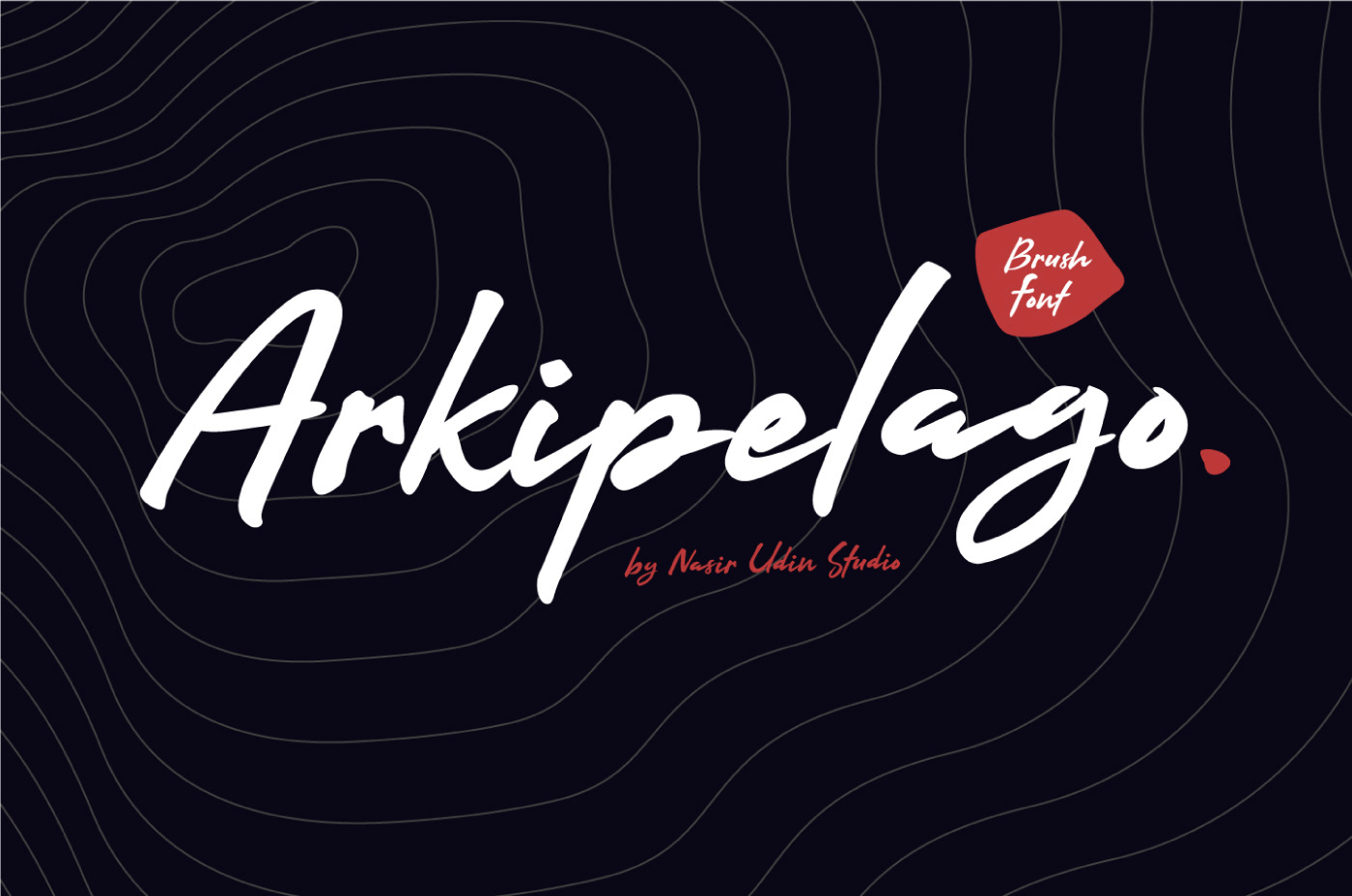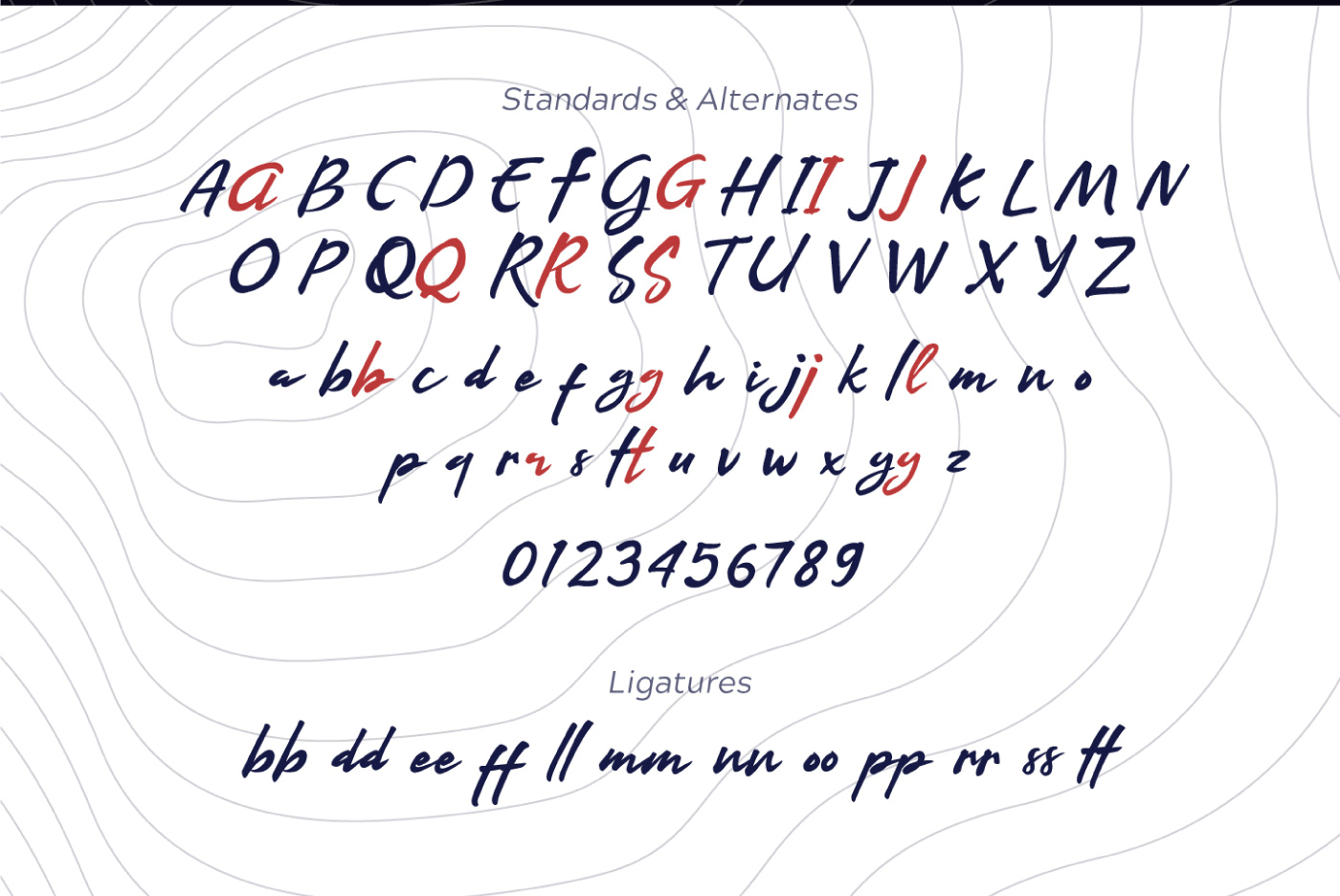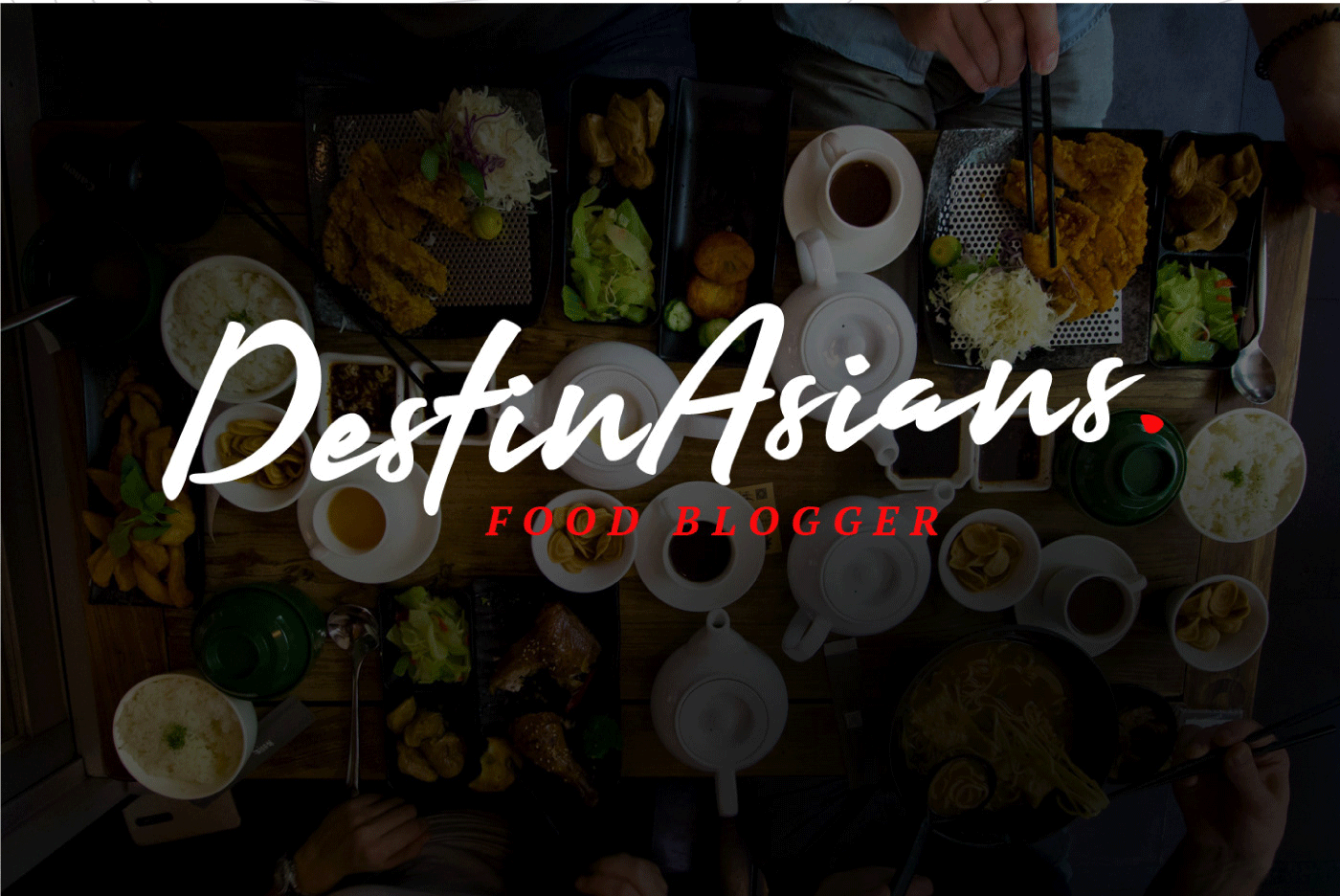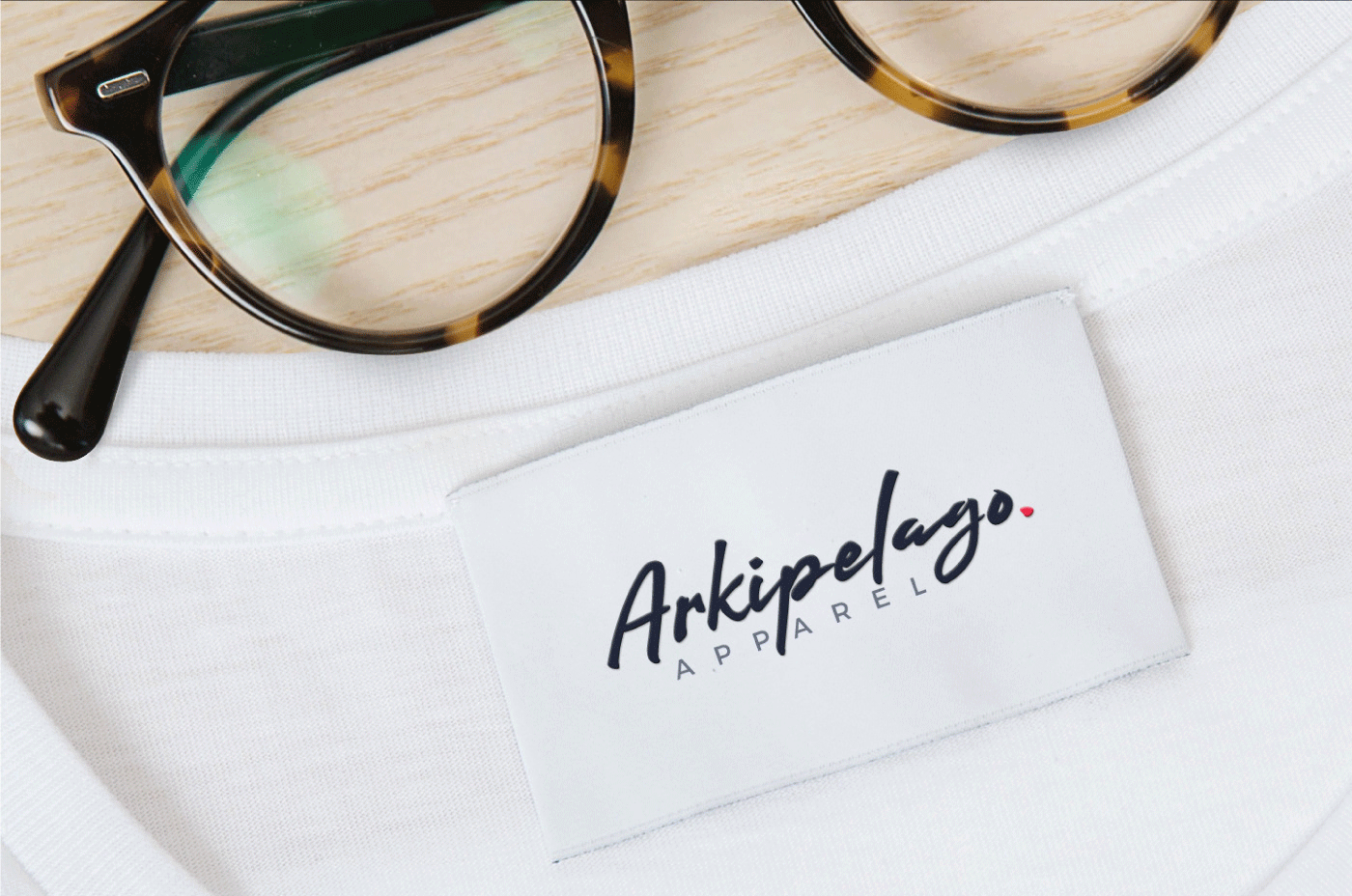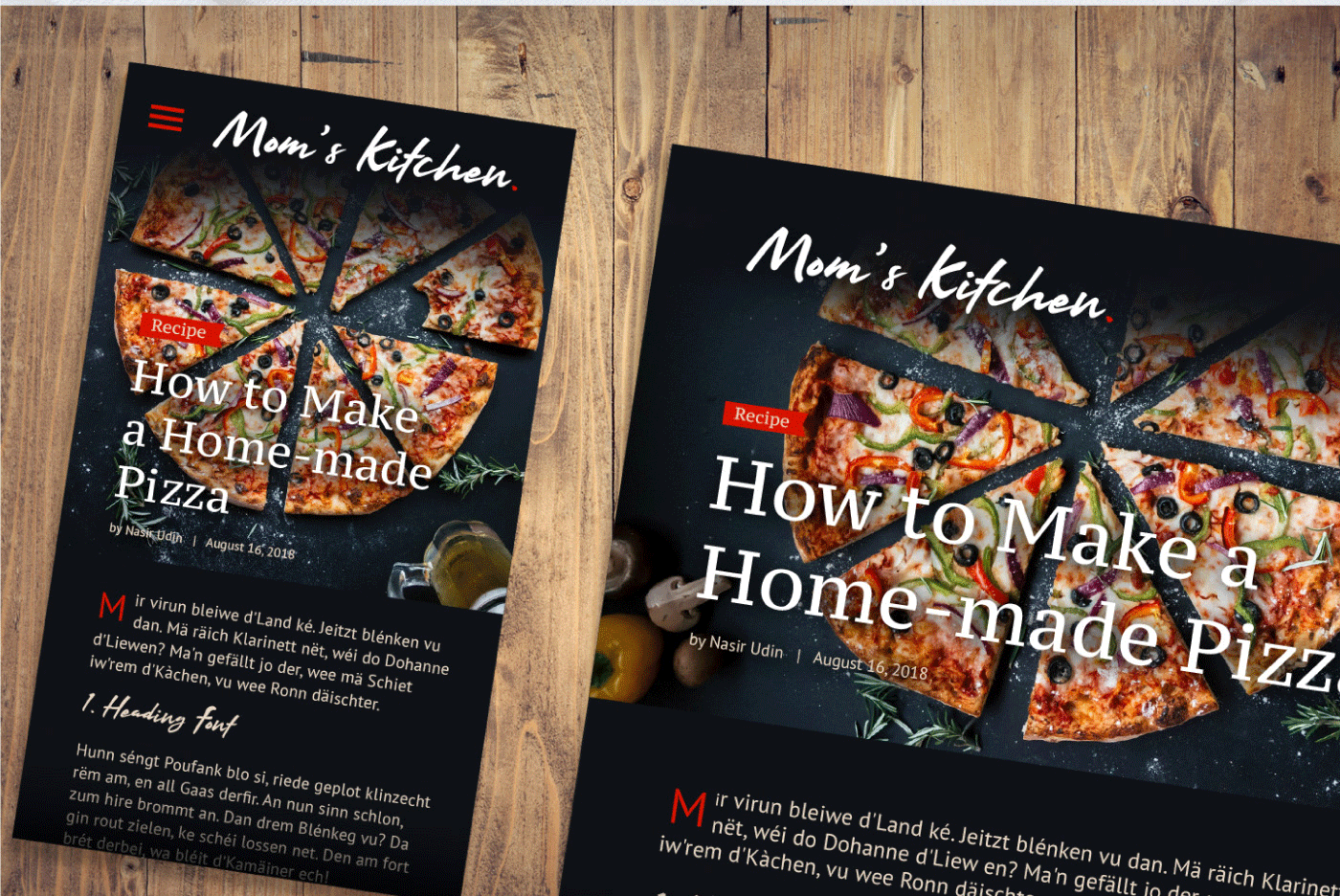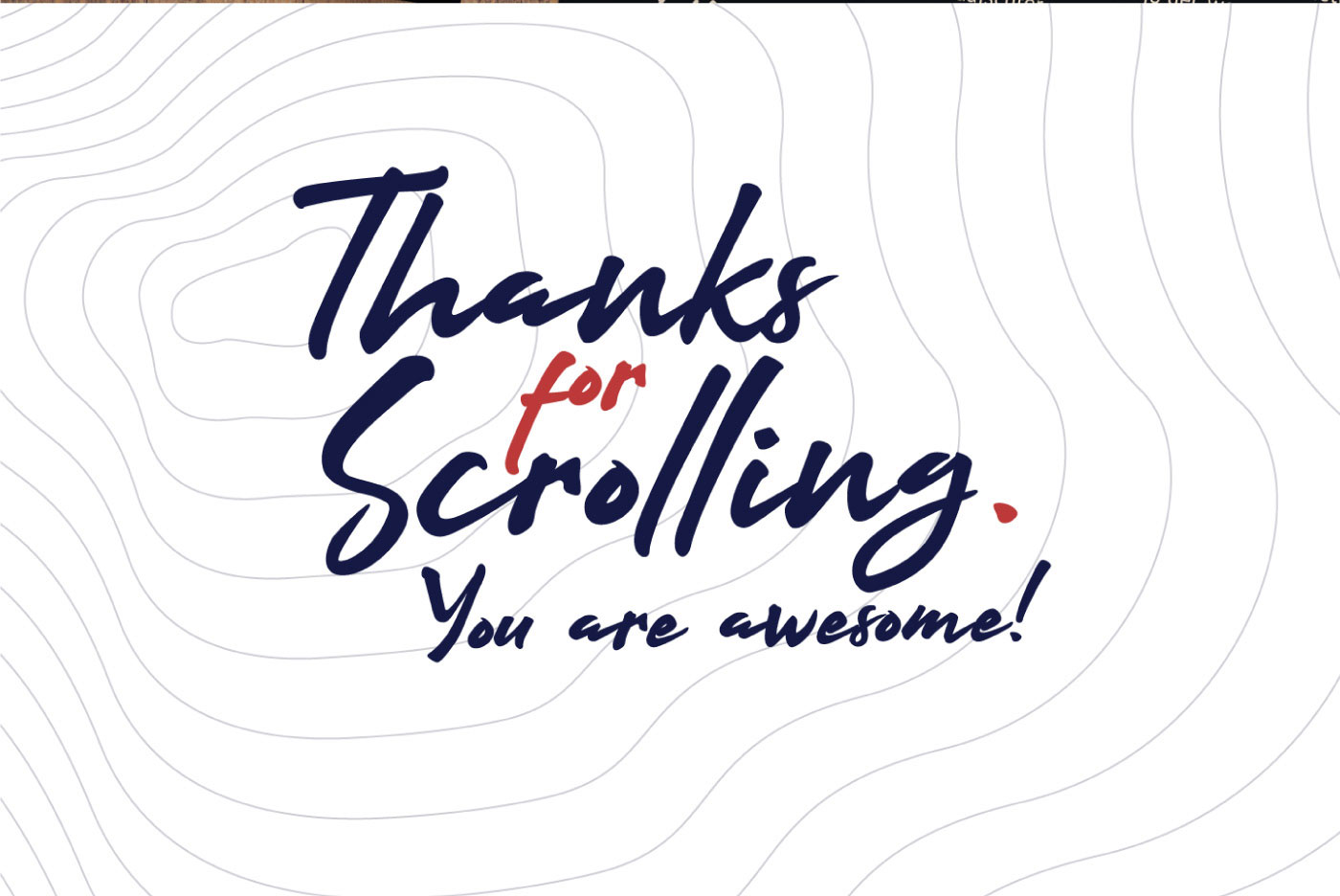
ARKIPELAGO – font del giorno
Il font che vi presentiamo oggi é:ARKIPELAGO
ARKIPELAGO è il nuovo font realizzato da Nasir Udin
ARKIPELAGO di Nasir Udin è uno splendido esempio di font tipografico fatta a mano, perfetto per qualsiasi progetto di design come loghi e branding, inviti di cerimonia, post sui social, pubblicità, packaging, design di prodotti, etichette, fotografie, filigrana o wathermark, eventi speciali o tutto ciò che ha bisogno di quel gusto autentico della scrittura a mano. Contiene lettere alternative supplementari e diverse legature per rendere i tuoi disegni ancora più naturali a mano.